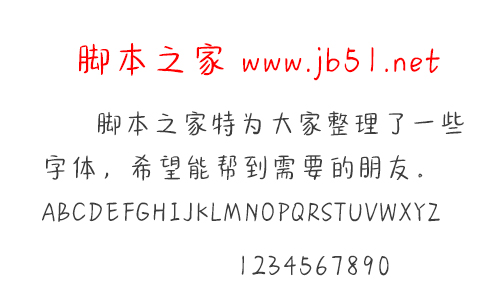
Aa我的初戀宇宙是Aa字庫中的一款手寫風(fēng)格藝術(shù)字體,風(fēng)格比一般的字體更有特色,連貫字跡顯得干練而不凌亂,清新簡明,具有很好的視覺感,適合應(yīng)用于藝術(shù)設(shè)計、平面宣傳設(shè)計、網(wǎng)頁設(shè)計,書法字帖等領(lǐng)域,歡迎喜歡此字體的朋友前來下載使用。